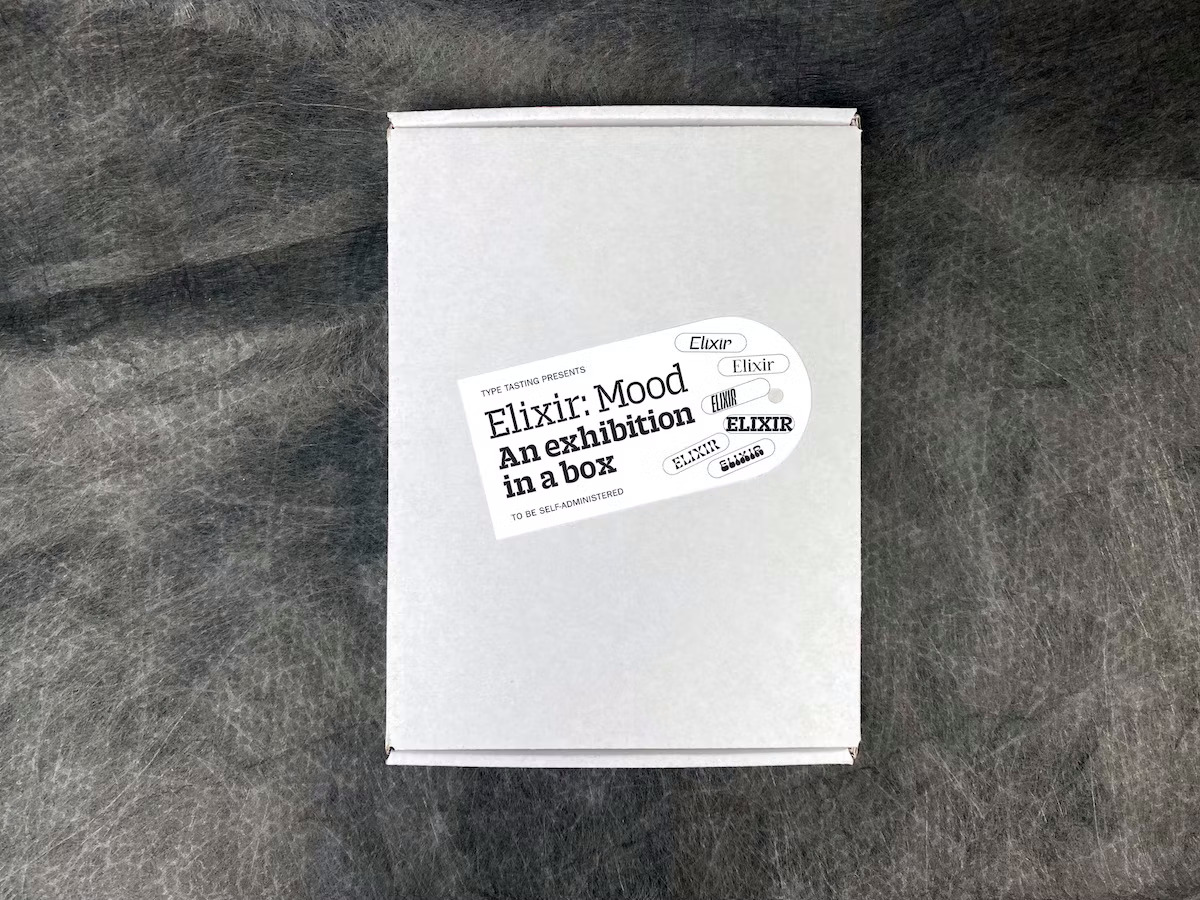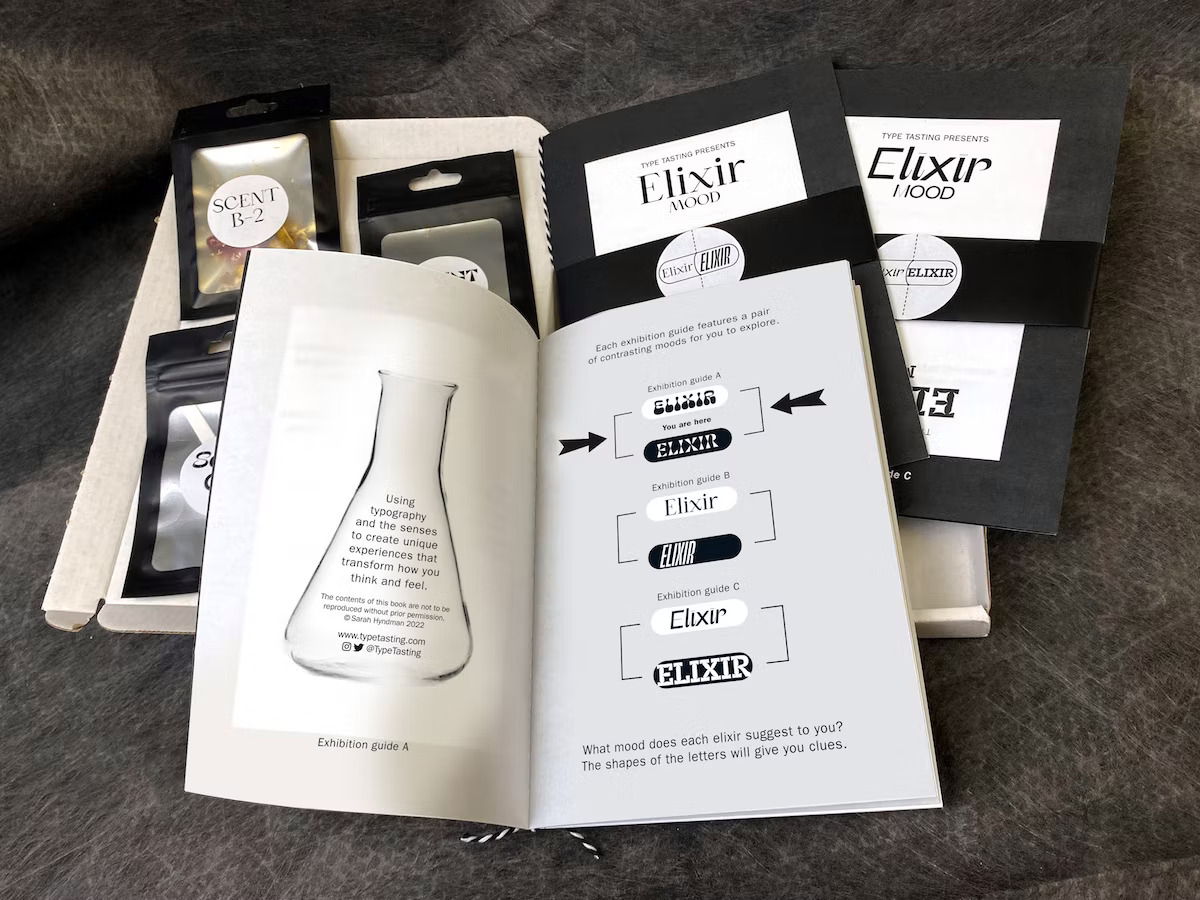
Esta exhibición demuestra el poder emocional de la tipografía
La exhibición está compuesta por tres revistas en blanco y negro que cuentan con diferentes tipos de letras que juegan con la idea de la luz y la oscuridad. Además, incluye actividades lúdicas y cuadros en blanco estilo álbum de recortes.
Sarah Hyndman, diseñadora y fundadora de la empresa Type Tasting y autora de “¿Por qué la tipografía importa?”, ha estado realizando experimentos y estudios para conocer el efecto de la tipografía en nuestro estado de ánimo y sentidos. Ahora, con la ayuda de una subvención del Consejo de las Artes del Reino Unido, ha creado una «exhibición» innovadora.
Titulado “Elixir: Mood”, el proyecto se describe como “una exhibición sensorial expansiva” que tiene como el objetivo de llevar a sus espectadores “en un viaje a diferentes estados de ánimo” a través del poder de la tipografía, el sonido, la imagen, la textura y el olor.
La exhibición, que se encuentra dentro de una caja, cuenta con una serie de tres revistas, así como tres bolsas pequeñas, cada una cuenta con un objeto que da un aroma diferente (uno tiene la forma de materia vegetal seca, otros se asemejan al perfume). Cada aroma corresponde a diferentes ejercicios, que también incluyen señales sensoriales como texturas para sentir, trampantojos tipográficos y enlaces a piezas de sonido.
El proyecto busca ayudar a las personas a “descubrir cómo usar más sus sentidos puede contribuir con la evocación de las emociones y crear una sensación de espacio”.
“Estos están diseñados para sacarte de tu día a día típico. Puedes interactuar con cada uno de los seis estados de ánimo a través del lenguaje, enlaces, texturas, olores y meditaciones tipográficas”, explica.
El diseño
El diseño de las revistas es todo en blanco y negro y cuentan con mucho tipo de letra. En ‘Elixir’, las páginas, como las formas de las letras, juegan con la idea de la luz y la oscuridad; y se presentan actividades lúdicas y cuadros en blanco estilo álbum de recortes, para que los usuarios los completen a medida que avanzan.
Es una versión inteligente del formato de exhibición en un mundo posterior al confinamiento, ya que es posible ver la exhibición desde tu propia casa (la caja la envían por delivery), también hace un buen uso de los códigos QR.
“El formato experimental explora los límites de una instalación, retirándola del espacio de exhibición tradicional”, dice Hyndman. “Las realidades se mezclan a medida que se difuminan las líneas entre lo físico y lo virtual… donde se encuentran lo tangible y lo intangible”.